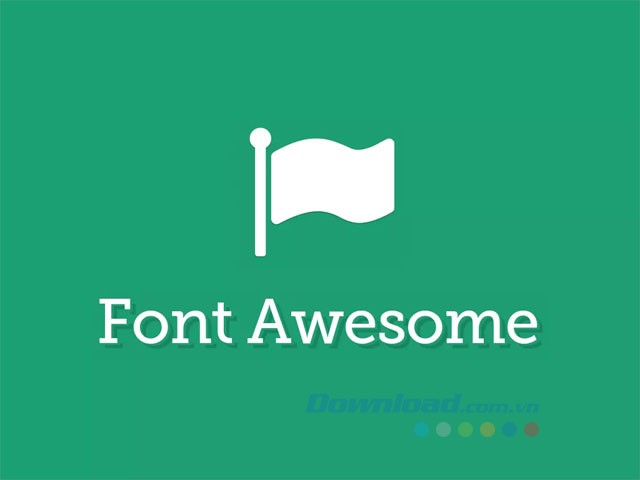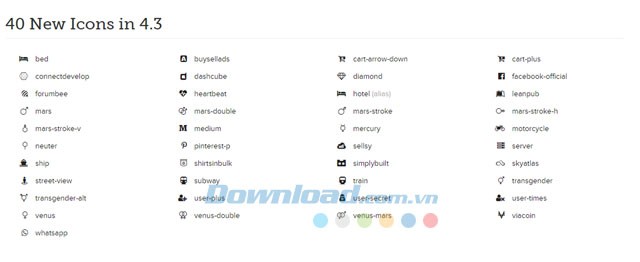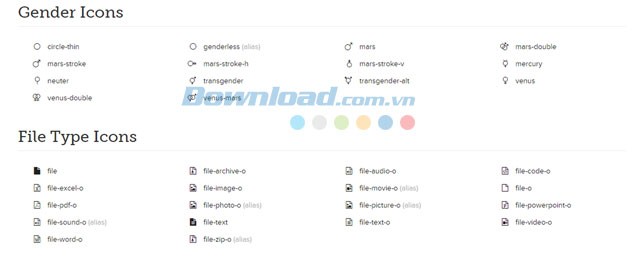
Font Awesome: Giải Pháp Icon Vector Hiệu Quả
Font Awesome là một công cụ hỗ trợ đắc lực, mang đến cho người sử dụng một thư viện phong phú các biểu tượng vector, phục vụ cho việc xây dựng blog hoặc website, phục vụ cả nhu cầu cá nhân lẫn công việc.
Trước khi có sự ra đời của công cụ này, việc chèn icon minh họa vào website thường gây ra nhiều khó khăn cho người dùng. Bạn cần phải tự tạo hình ảnh, tinh chỉnh CSS để đảm bảo chúng hiển thị đúng như mong muốn.
Việc thay đổi kích thước icon cũng đòi hỏi phải tạo một hình ảnh mới, gây ra sự bất tiện không nhỏ. Điều này đặc biệt khó khăn đối với những người viết web chỉ nắm vững kiến thức cơ bản về HTML, CSS, Javascript mà không có kinh nghiệm trong lĩnh vực thiết kế đồ họa.
Font Awesome giúp người dùng dễ dàng tích hợp các biểu tượng thông qua CSS, mà không cần đến Javascript hay bất kỳ công cụ hỗ trợ nào khác. Đồng thời, việc sử dụng hình ảnh để thiết kế website hay blog cũng trở nên không cần thiết.
Công cụ này hỗ trợ đa dạng các kiểu icon, ví dụ như icon mũi tên có thể chỉ hướng sang phải, trái, lên trên hoặc xuống dưới, chỉ bằng cách điều chỉnh CSS.
Một lợi thế vượt trội của chương trình này là khả năng tùy biến icon mà không gây ảnh hưởng đến tốc độ tải trang web. Người dùng có thể thay đổi màu sắc, hiệu ứng của icon... một cách tự do, tương tự như thao tác với một ký tự thông thường, mà không cần lo lắng về tác động tiêu cực đến hiệu suất trang web.
Những Ưu Điểm Vượt Trội của Font Awesome
Font Awesome sở hữu một kho tàng biểu tượng (icon) phong phú, hiện nay đã hỗ trợ hơn 519 icon đa dạng, đáp ứng mọi nhu cầu thiết kế.
Điểm đặc biệt khác là Font Awesome không đòi hỏi bất kỳ đoạn mã Javascript nào để hoạt động, giúp tối ưu hiệu năng trang web.
Khả năng tùy biến của Font Awesome là vô hạn, cho phép người dùng điều chỉnh mọi khía cạnh chỉ bằng CSS, mang đến sự linh hoạt tối đa trong thiết kế.
Giao diện của Font Awesome được thiết kế thân thiện, dễ sử dụng, phù hợp với cả người mới bắt đầu và các nhà thiết kế chuyên nghiệp.
Kích thước của các icon có thể được điều chỉnh một cách dễ dàng, không giới hạn, phù hợp với mọi bố cục và kích thước màn hình.
Font Awesome được tối ưu hóa để hiển thị sắc nét và rõ ràng trên các màn hình Retina, mang lại trải nghiệm thị giác tuyệt vời.
Thư viện này tương thích với hầu hết các framework phổ biến hiện nay, giúp tích hợp dễ dàng vào các dự án web khác nhau.
Font Awesome còn tích hợp khả năng đọc màn hình (screen reader), đảm bảo khả năng tiếp cận cho người dùng khiếm thị.
Lợi ích của việc ứng dụng Font Awesome
- Việc sử dụng Font Awesome giúp giảm thiểu thời gian và nỗ lực cần thiết cho quá trình thiết kế các biểu tượng (icon).
- Dung lượng trang web có thể được giảm đáng kể khi sử dụng Font Awesome thay thế cho các phương pháp tạo icon truyền thống.
- Khả năng tùy biến linh hoạt cho phép người dùng dễ dàng điều chỉnh kích thước icon, phóng to hoặc thu nhỏ theo yêu cầu.
Tốc độ tải trang ổn định cùng với vô số tùy chỉnh thu hút đã khiến Font Awesome trở thành một công cụ được ưa chuộng trong cộng đồng thiết kế web và xây dựng blog hiện nay.
Sự phổ biến của Font Awesome còn đến từ khả năng tương thích rộng rãi với nhiều nền tảng và framework khác nhau.
Font Awesome không chỉ cung cấp các icon cơ bản mà còn có nhiều bộ icon chuyên dụng cho các lĩnh vực khác nhau.
Nhờ đó, người dùng có thể dễ dàng tìm thấy các icon phù hợp với chủ đề và mục đích của trang web.
Hơn nữa, Font Awesome liên tục được cập nhật với các icon mới, đáp ứng nhu cầu ngày càng cao của người dùng.
Việc sử dụng Font Awesome còn giúp cải thiện trải nghiệm người dùng, làm cho trang web trở nên trực quan và hấp dẫn hơn.
Các biểu tượng được thiết kế đẹp mắt và chuyên nghiệp, góp phần nâng cao giá trị thẩm mỹ của trang web.
Tóm lại, Font Awesome là một công cụ hữu ích và đáng tin cậy cho bất kỳ ai muốn tạo ra một trang web đẹp mắt và hiệu quả.